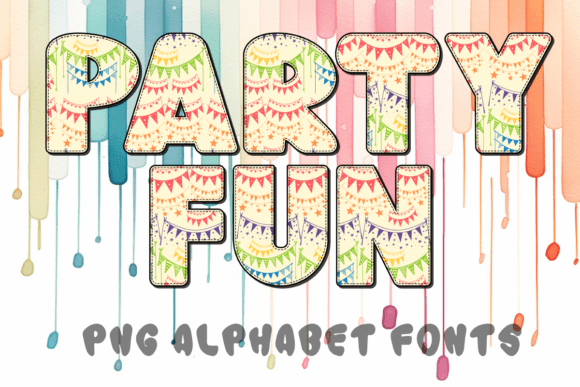
Party Fun Alphabet Fonts
Party Fun Alphabet Fonts – A Fonte Perfeita para Celebrar Cada Detalhe!
Se você está à procura de uma tipografia que transforme convites, banners e postagens nas redes sociais em verdadeiras festas visuais, o Party Fun Alphabet Fonts é a escolha certa. Este conjunto digital traz 26 letras maiúsculas e 10 números (0‑9) com desenhos divertidos e cheios de energia, prontos para dar aquele toque festivo que todo projeto merece.
- Design exclusivo e animado – Cada letra e número foi criado com elementos coloridos e desenhados à mão, garantindo originalidade.
- Versatilidade total – Perfeitos para convites de aniversário, festas temáticas, cartazes, banners, stories do Instagram, e muito mais.
Por que escolher o Party Fun Alphabet Fonts?
Além de sua aparência vibrante, este pacote oferece economia de tempo para designers que precisam de resultados rápidos e impactantes. Cada caractere foi pensado para se destacar em fundos claros ou escuros, e a transparência dos PNGs elimina a necessidade de recortes adicionais.
Aplicações Ideais
- Convites digitais ou impressos para aniversários, festas infantis e eventos corporativos.
- Banners e flyers promocionais para lojas, clubes e eventos temáticos.
- Posts e stories nas redes sociais que precisam de um visual alegre e chamativo.
- Materiais de marketing como cartões de visita, etiquetas e adesivos personalizados.
Com o Party Fun Alphabet Fonts, a criatividade ganha um impulso extra de cor e diversão. Seja para profissionais de design ou para quem cria projetos caseiros, este conjunto entrega qualidade, praticidade e um toque festivo que faz qualquer peça se destacar. Não perca tempo – adicione já ao seu arsenal criativo e deixe a festa começar!